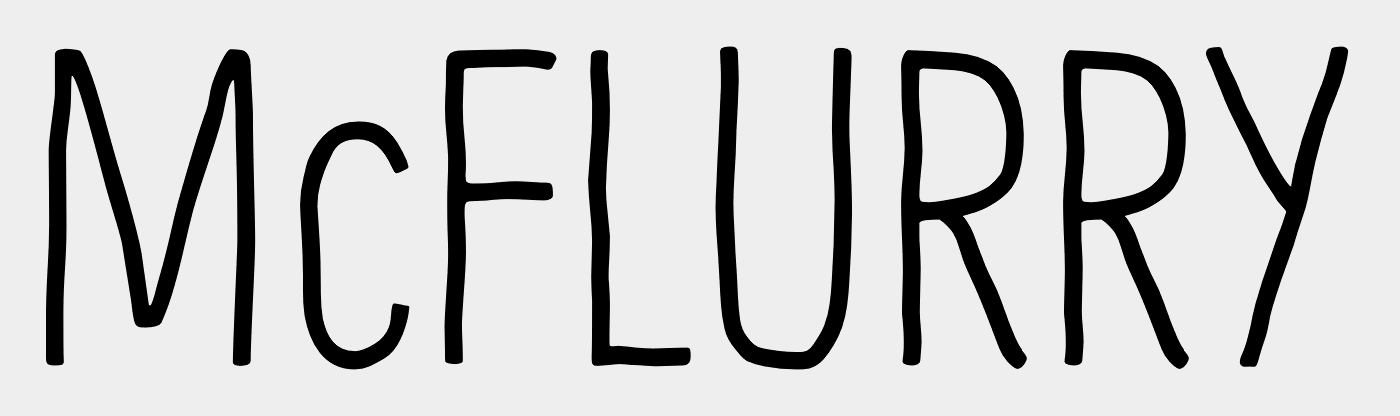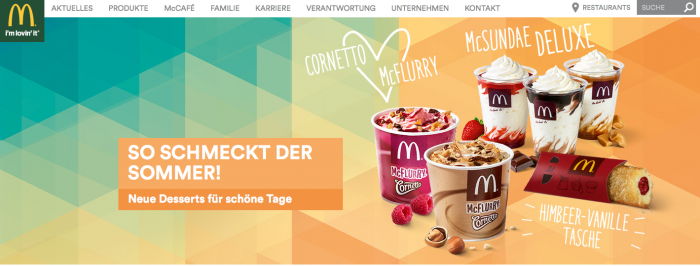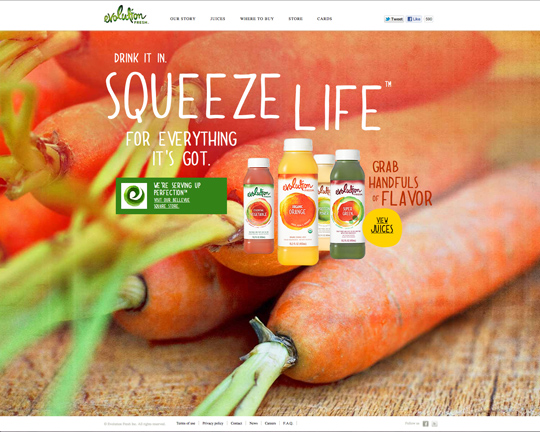
Welche handgeschriebenen Schriftarten sind das?
McDonalds Webseite: Produktnamen
Evolution Juice Plakat: Alle Slogans/Texte
MPreis Plakat: Schriftzug
Weißt du, ob es für diese Art von Schriftarten einen Oberbegriff gibt? Handwritten währe wohl zu allgemein, da dann ja script Schriftarten auch dazugehören würden. Diese Schriftarten sind alle von ihren Eigenschaften wie x-height, width, san serif eigentlich sehr ähnlich zu den klassischen text-Schriftarten wie Helvetica.
i am just wondering how this type of fonts distiguishes from fonts like honeyscript, which look way more curved and like script. i guess both are handwritten, but there is a huge difference between them.
Bene, that goes for other "groups" too... a tag like script includes for instance Balmoral and Vivaldi; very different type.
Usually solved by multiple tags.
Here's a basic piece about classification:  https://en.wikipedia.org/wiki/Vox-ATypI_classification
And as germans always do it "gründlich": https://de.wikipedia.org/wiki/DIN_16518  (no offence intended)
The classification systems have worked fine in the pre digital era because print plants had only a few typefaces to choose from (them trays with lead sure weighed a bit and took a lot of space, hence even a limited number of corps).
Since entering the digital era the number of typefaces has exploded and become quite affordable (even free) for everyone compared with letterpress but the standard classification still work on them.
Redefining characteristics on a gazillion typefaces will also be a hell of a job, probably not finished in a lifetime.
Es gibt wie immer keine exakte und allumfassende Definition dieser Art von Schriften. Du kannst aber verschiedene Eigenschaften genau beschreiben und kombinieren.
* Handschriftliche Antiqua (handwritten, handdrawn) ist eine sehr grobe und ungenaue Einordnung nach DIN 16518
* Einige dieser Schriften bestehen nur aus Großbuchstaben, dass nennt man Blockschrift (block letters, all caps, small caps)
* Einige dieser Schriften sind sehr hochgewachsen, daher Condensed und/oder Tall
* Diese Schriften sind aufrecht und daher nicht als Script im eigentlichen Sinn zu deklarieren
Du musst daher die Suchbegriffe handwritten oder handdrawn, block letters oder all caps oder small caps  und condensed oder tall kombinieren. Also [handwritten|handdrawn] & [block letters|all caps|small caps] & [condensed|narrow|tall]. Du brauchst von den Begriffen in den eckigen Klammern immer nur einen. Aber dieser ist auch abhängig von der jeweiligen Datenbank. Ich bringe Dir ein paar Beispiele. Bei denen siehst Du das Schriftenhörnchen handdrawn benutzt, aber Mayfonts.com und viele andere handwritten.
Beispiel: Schriftenhörnchen mit handdrawn & all caps:
Beispiel: Schriftenhörnchen mit handdrawn & all caps & narrow:
Beispiel Myfonts.com mit Tags handwritten & narrow:
Wenn Du dir bei Myfonts dann eine der Schriften ansiehst findest Du auf der Seite weitere public Tags, von denen das eine oder andere durchaus auch brauchbar ist. Beispiel: Illustration.
Beispiel Myfonts.com mit Tags handwritten & narrow & illustration:
Bei diesen Beispielen sind mindestens 2/3 der angezeigten Schriften aus dieser Gruppe von Schriften und die hier gesuchten Schriften tauchen da auch auf. Es tauchen aber trotzdem einige Script auf, welche da IMHO nicht rein gehören, da diese eine eigene und angegrenzte Klasse sind. Ich hoffe das reicht als kleine Anleitung zur erfolgreichen Suche nach solchen Schriften.